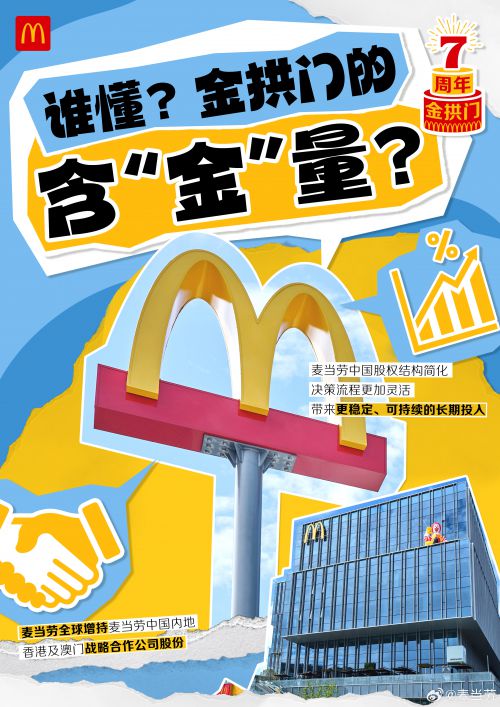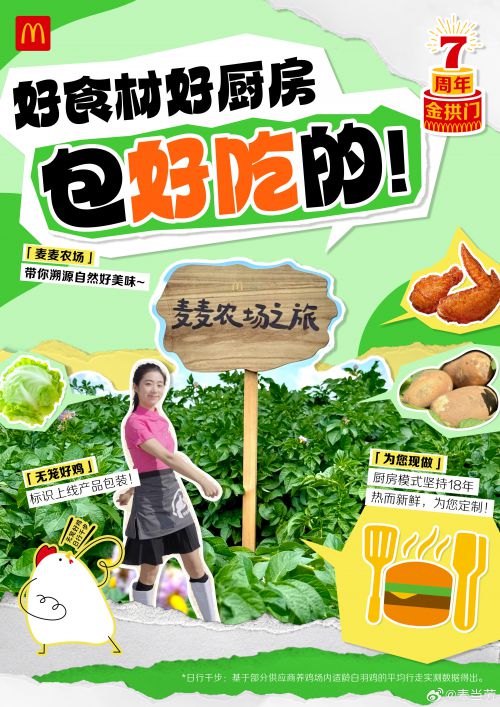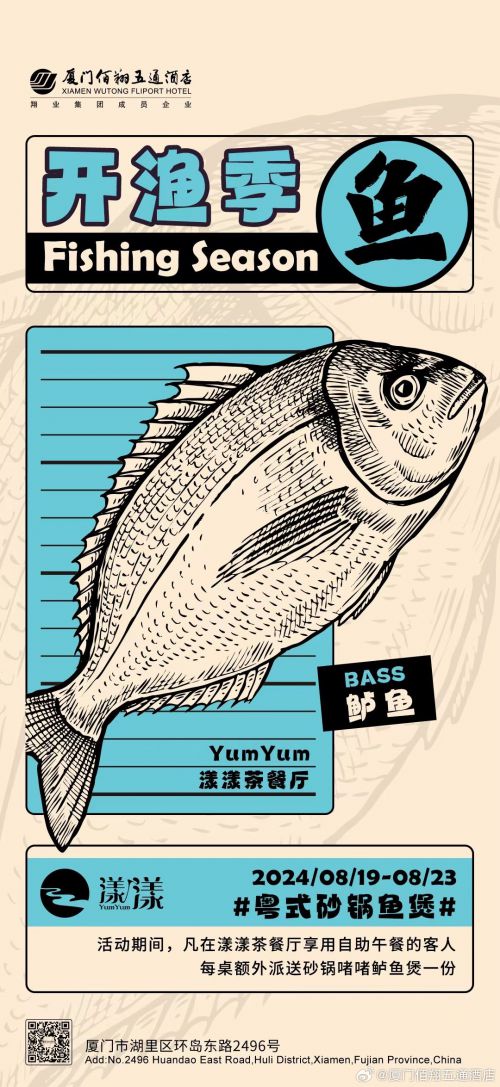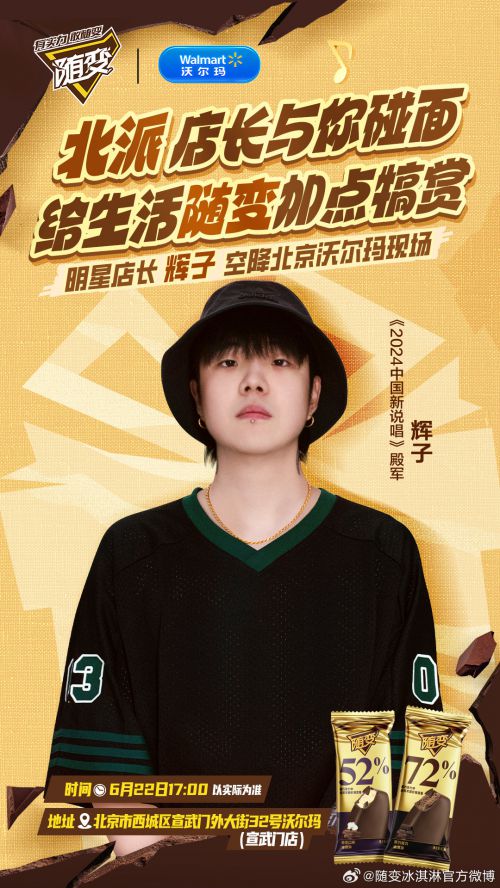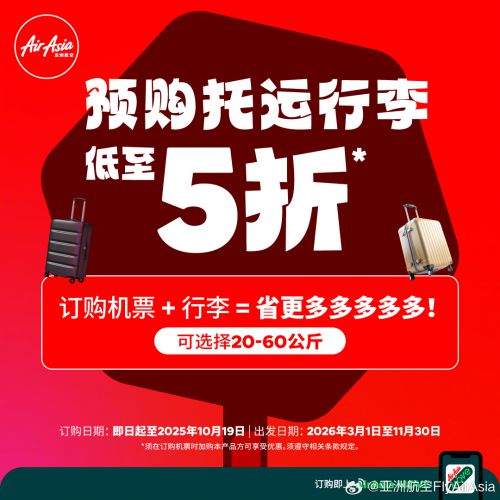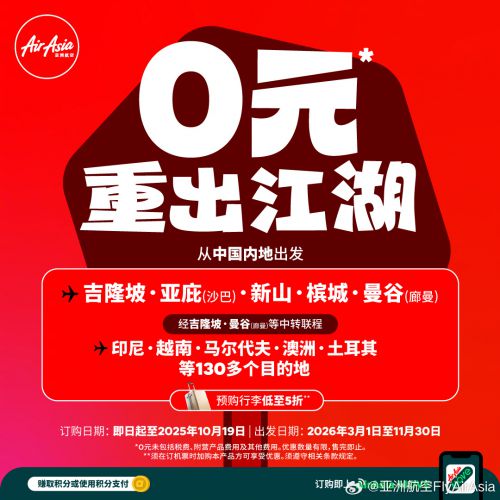
【点字灵动体】是点字库推出的创意黑体字库,以卡通可爱的设计风格和会员商用授权模式,成为视觉设计领域的灵动之选。字体采用扁宽字形设计,中宫宽博稳重,配合全圆角处理的圆头笔画,形成憨态可掬的视觉印象。粗壮均匀的笔画融合几何图形设计感,连笔结构与撇捺的灵动弧度增强趣味性,倾斜姿态更添活泼气质。 作为超粗字重的创意黑体,点字灵动体兼具块面冲击力与日式美学特质,适用于广告标题、产品包装、影视海报等需要快速吸引眼球的场景,尤其适合儿童用品、潮流品牌及日式主题设计。其醒目的视觉张力与可爱属性,能有效提升设计作品的传播力和记忆点。
卢鑫亚
90后字体设计师,曾获第二届字体之星评委奖,最具商业潜力奖,第三届字体之星评委奖。